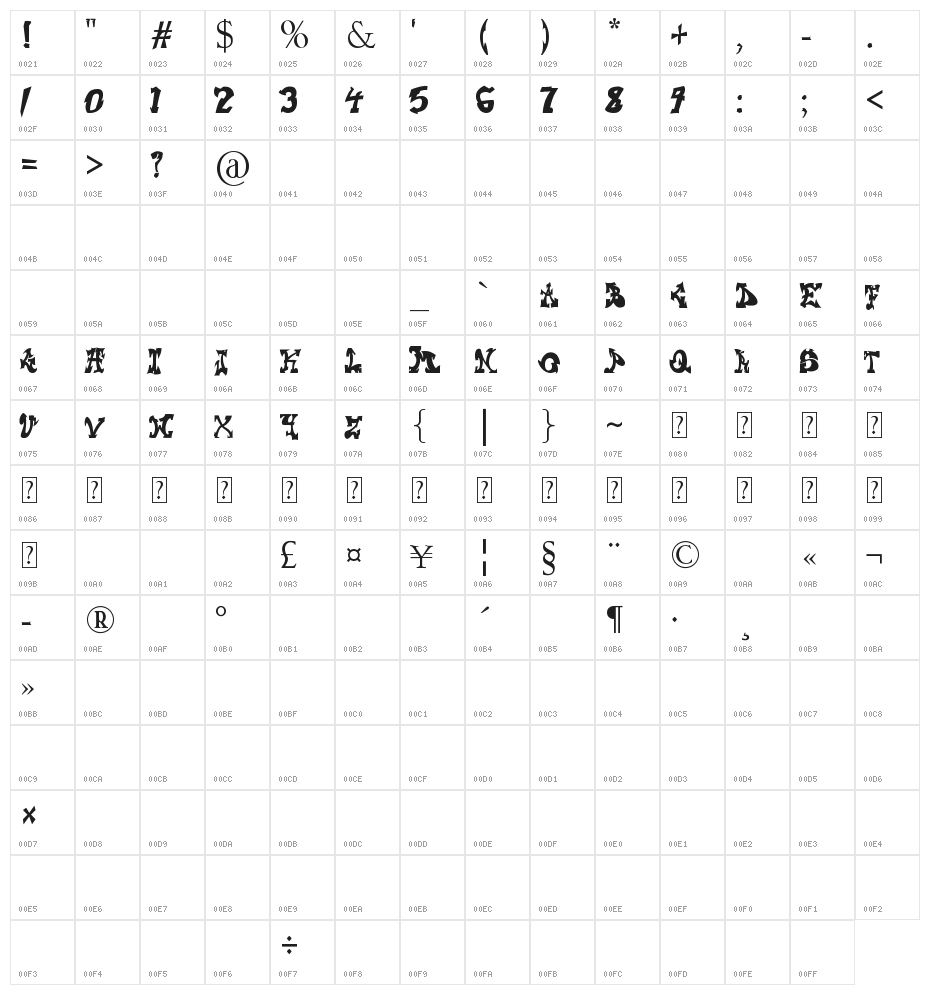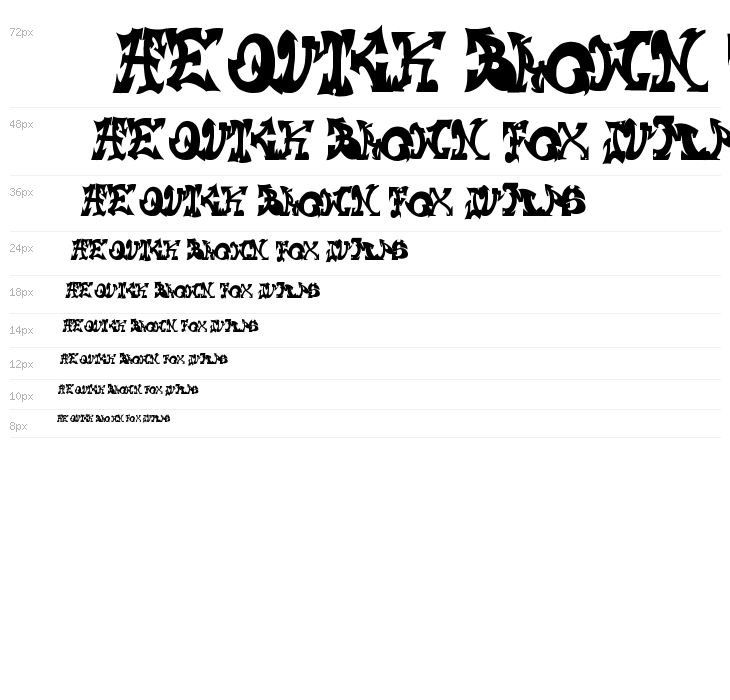
personal bj Font
✎ Graffiti
| Proiecte propuse | Ideal for use in graphic design projects that require a bold statement, such as posters, album covers, or branding for edgy or alternative products. |